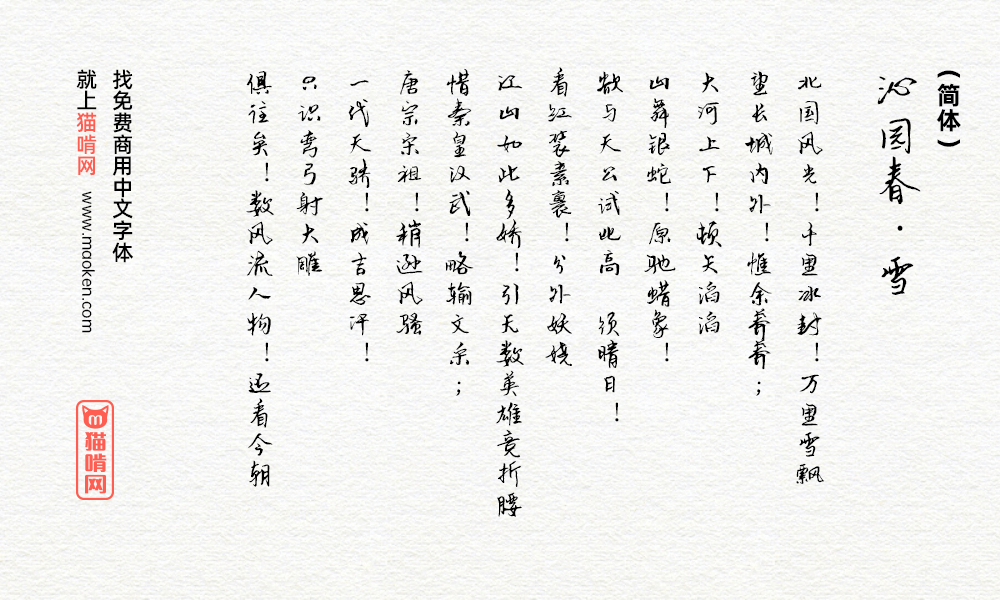
缘缘体行书:行云流水潇洒自如的手写体
字体作者:姿善 (中国大陆) 字体字重:1个
缘缘体行书是由大美女姿善的手写的一款字体,由广西霁云轩字体工作室制作成字体文件分享给大家使用。这是一款适用于艺术设计方面的手写字体,字型十分漂亮。延续了行书的行云流水,添加了自己的特色,潇洒自如,简单大方,看上去很整齐,无拘无束,适用于广告设计、装潢设计、视觉设计等。